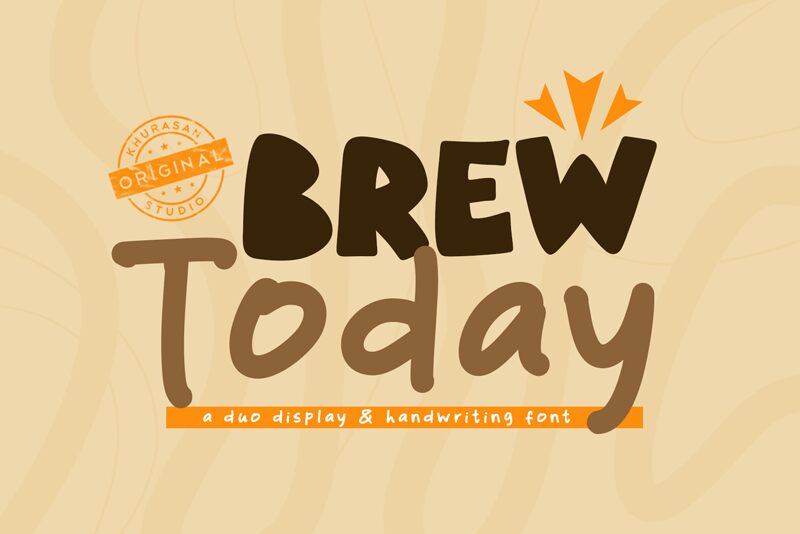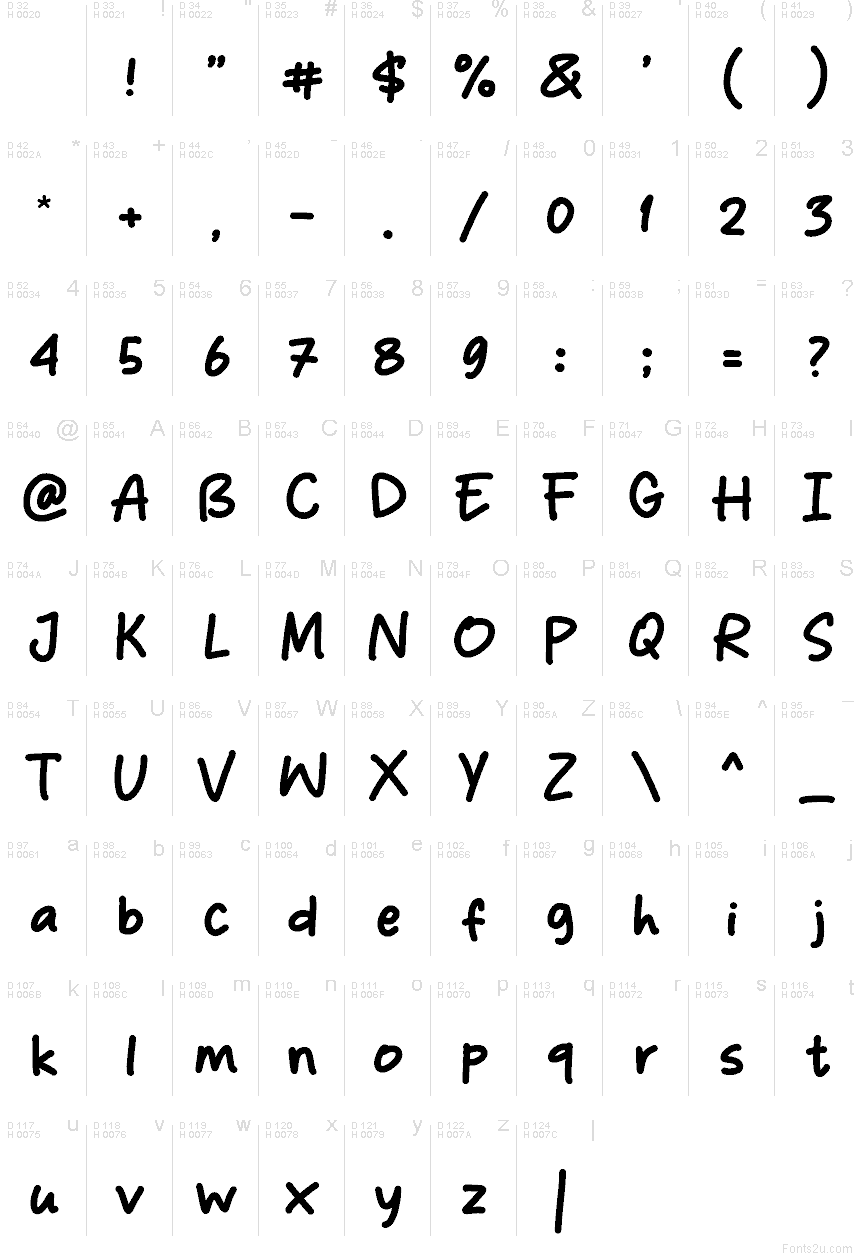
Brew Today HW von Khurasan ist eine kostenlose handschriftliche Display-Schrift mit breiten, gerundeten Strichen und einem unkomplizierten, handgezeichneten Look. Ihre unregelmäßigen Kurven, weich abgeflachten Enden und lebhaften Strichstärkenwechsel verleihen dem Schriftbild eine schnelle und persönliche Note.
Unabhängige Cafés und zwanglose Food-Marken können sie für Logos, Verpackungen und Speisekarten einsetzen, um eine warme, informelle Atmosphäre zu schaffen. Die Buchstaben wirken wie handgemacht. Ihre vollen Kurven und markerähnlichen Enden eignen sich zudem hervorragend für fröhliche Getränkeillustrationen, wodurch Namen zu einem Teil des gezeichneten Kunstwerks werden.